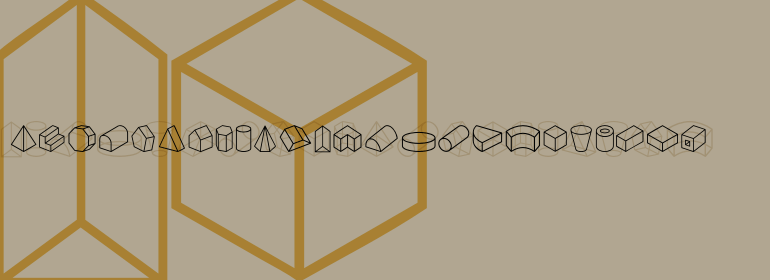
Linotype Shapeshifter™
Linotype Shapeshifter™,这款字体结构工整、笔画清晰,兼顾美观与易读性,适用于标题、正文、海报、包装、LOGO 等多种场景。字形优雅稳定,风格百搭耐看,适配日常排版与创意设计,让文字呈现更舒适、更具质感。Linotype Shapeshifter™一笔一画,皆是细节,以均衡的比例、流畅的线条打造舒适视觉体验,字形端正大气,风格简约现代。无论是商业设计、品牌宣传还是日常排版,都能轻松驾驭,让文字更有格调与力量。Linotype Shapeshifter™字体下载。